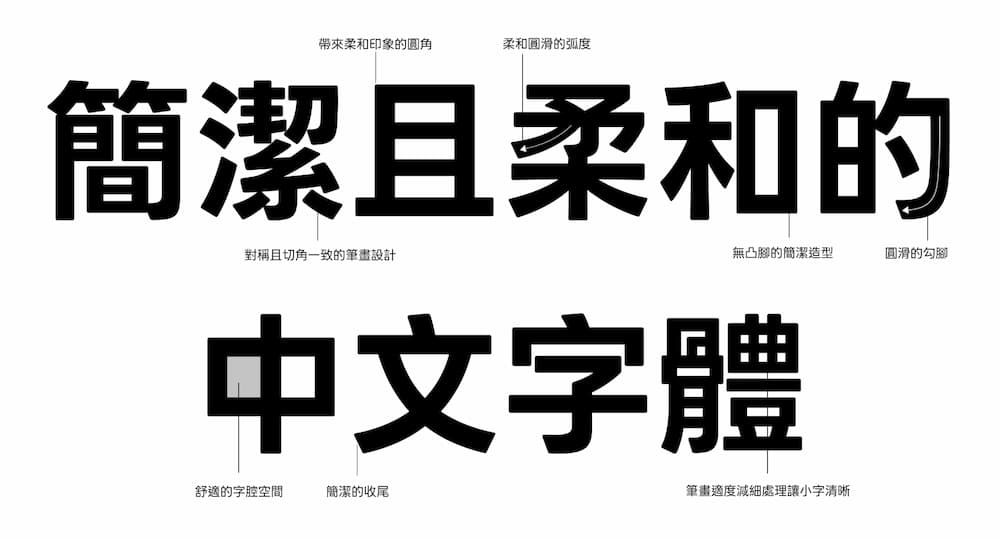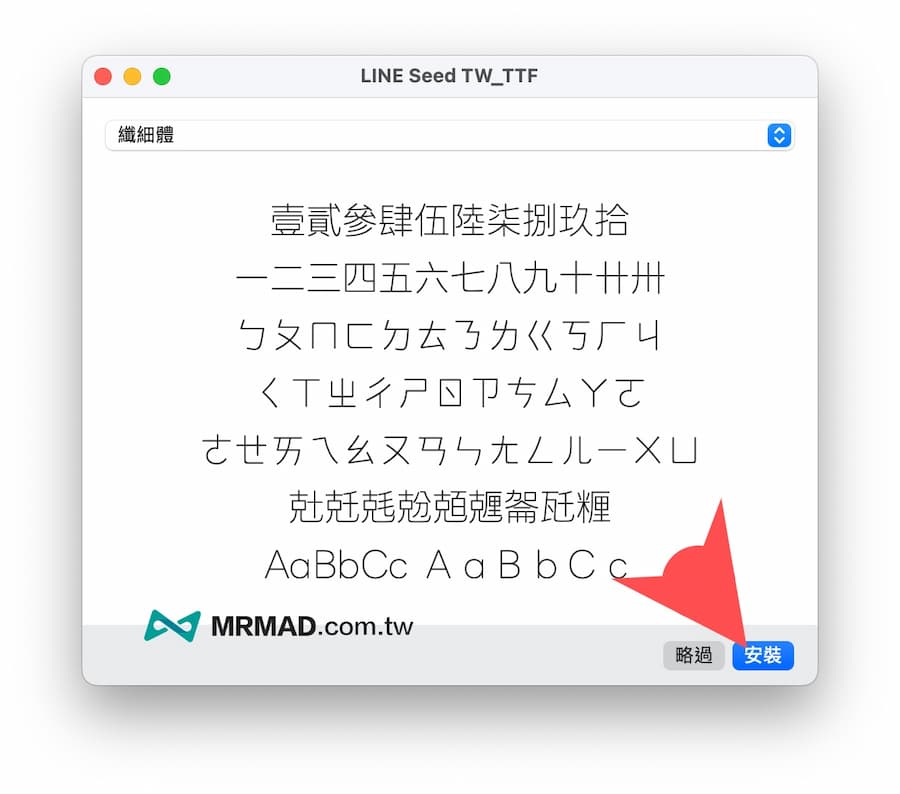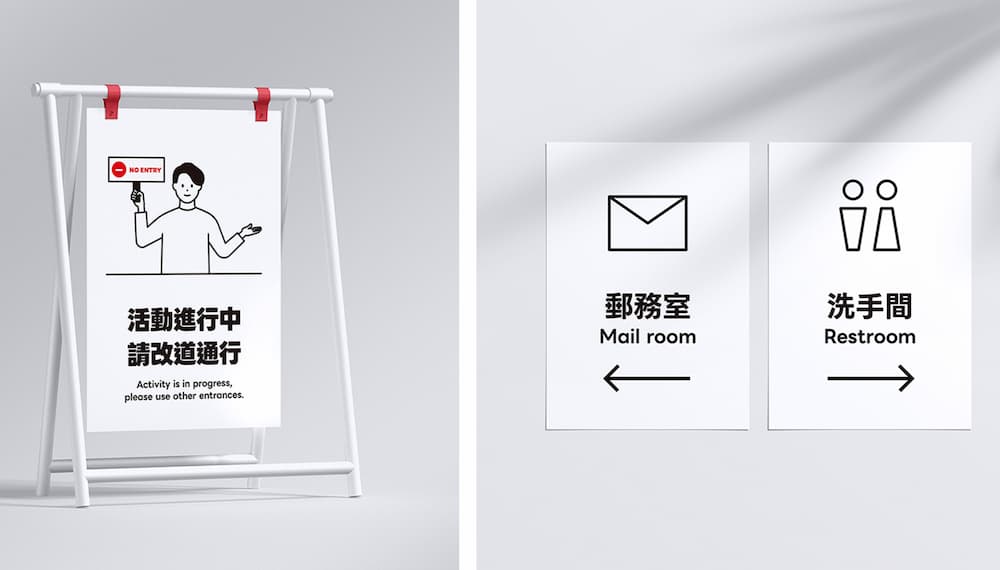
LINE官方近日正式推出自家全新LINE企業字體「LINE Seed 繁體中文版(LINE Seed TW)」,同時開放LINE字體免費下載使用,此次釋出的字型提供四種不同粗細字重,不僅能自由用於個人專案,也允許商業用途,適用範圍涵蓋貼圖設計、簡報製作、品牌視覺、社群圖卡與印刷品等多元場景。
LINE免費字體「LINE Seed」是由 LINE 內部團隊主導設計,並已陸續開發多國語言版本,這次釋出的繁體中文版也是由 LINE 攜手華康字型合作打造,共收錄 14,038 個字符,以日文字型為基礎延伸,承襲英文版的圓角幾何設計語言,並融入 LINE 品牌標誌性的視覺元素。
官方強調,LINE新字型希望能讓文字「看起來舒服、讀起來親切」,進一步拉近與使用者之間的距離。
在應用層面上,LINE Seed 繁體中文免費字體也具備高辨識度與良好的中英文混排效果,對於內容創作者、品牌行銷設計師、甚至 LINE 貼圖作者而言,都是極具實用性的免費字型資源。